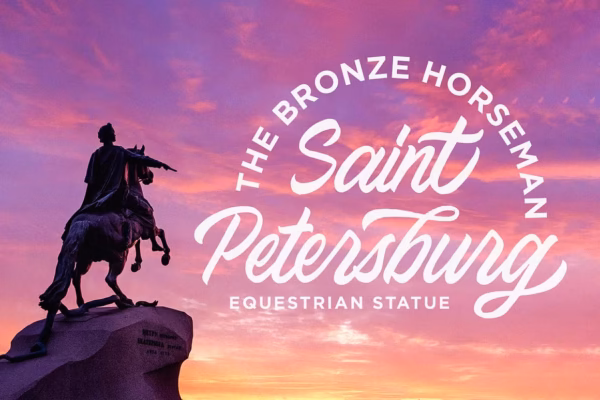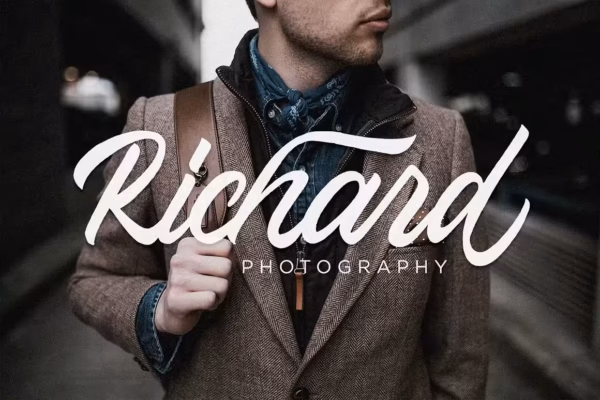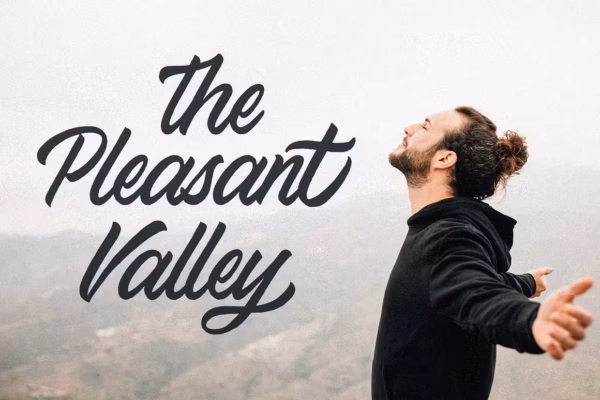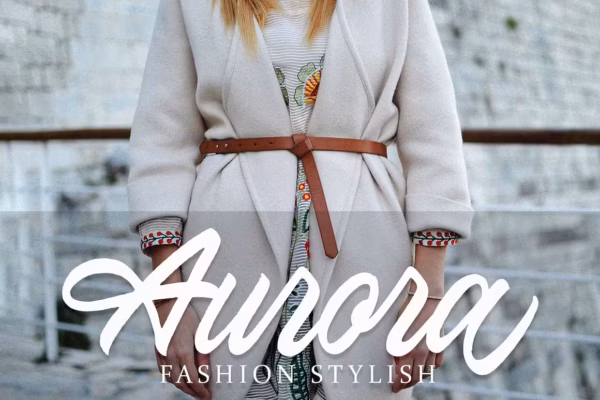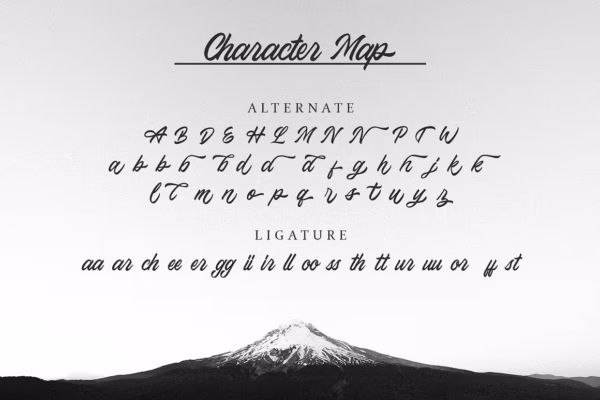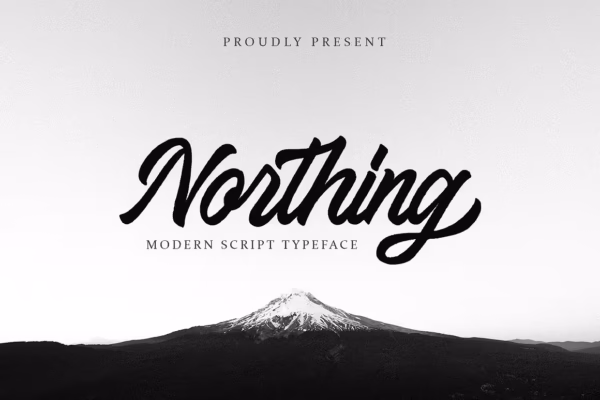
فونت اسکریپت مدرن Northing
Northing یک فونت اسکریپت مدرن و چشم‌ نواز با ظاهری طبیعی و حس نوشتار خودمانی است. این فونت برای استفاده در برندینگ، طراحی لوگو، لترینگ، لوگوتایپ، طراحی پوشاک، پوستر، مجله، بسته‌بندی، کیسه‌های خرید، تیشرت، جلد کتاب، پروژه‌های عکاسی، رویدادهای ویژه و سایر پروژه‌های طراحی، انتخابی ایده‌آل است.
ویژگی‌ها:
• حروف بزرگ و کوچک انگلیسی (Uppercase & Lowercase)
• اعداد
• علائم نگارشی (استاندارد OpenType)
• کاراکترهای چندزبانه و حروف دارای اعراب
• لیگچرها (Ligatures) و مجموعه‌های استایل جایگزین